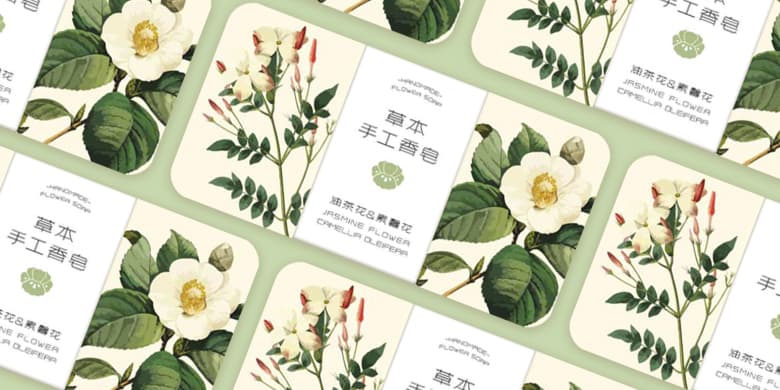
品牌:方正字库设计师:姜鹏飞发行时间:2019字库编码:大陆简体(GB2312-80)分类:创意字体字体属性:精品字
作者秋刀鱼,本名姜鹏飞,这款字体的灵感来自于一首古诗《相思》,意在表现一种传统委婉的情感,作者早些年做过一篇字体设计帖子,以文字与海报的形式结合,去体现传统之美。后来经过不断尝试与优化,最终确定将它做成一套完整的字库,其字为黑体大形,结构宽扁,重心平稳,笔画纤细温润,给人典雅平和的感觉,故取名润黑体,一些笔画的设计参考隶书的感觉,整体有传统古朴的韵味。